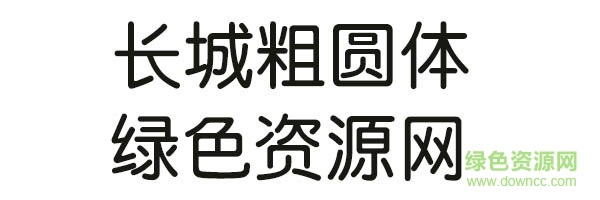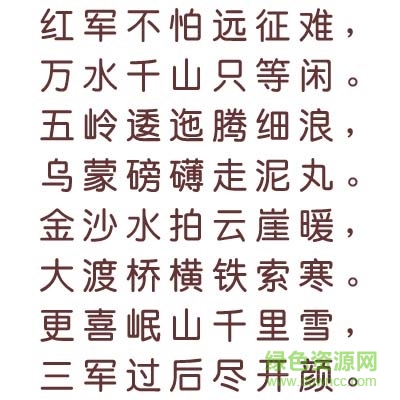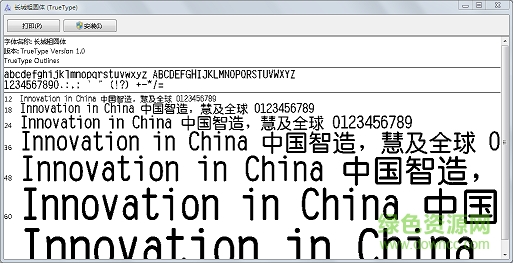
長城粗圓體是一款筆畫較粗,并且腳邊是圓形的簡體字體,不論是廣告設(shè)計,還是藝術(shù)創(chuàng)作中,都經(jīng)常用到。趕快到綠色資源網(wǎng)下載體驗(yàn)吧!
長城粗圓體字體圓鼓鼓的形態(tài)會為你一種可愛的感覺,并且略微的優(yōu)點(diǎn)加粗的效果,是越看越好看的字體